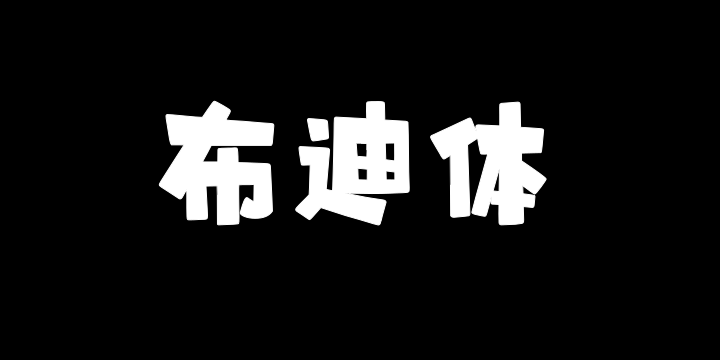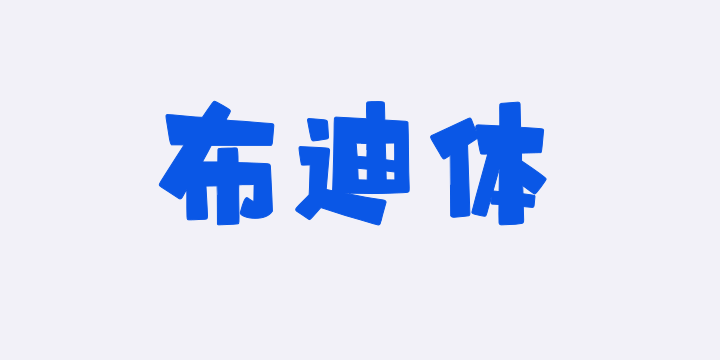
字体全名: 上首布迪体
铸字厂: 上首造字
设计师: 胡博剑
字体简介: 上首布迪体,简体中文约6763字,字体以pop字体为原型参考,字形设计注重动态感与趣味性,常通过拉伸笔画、立体效果和幽默造型吸引注意力。例如,活体字笔画向内聚拢,半包围结构字体需营造“馅比皮大”的视觉效果。 简洁性 信息传达需一目了然,避免复杂结构导致辨识困难。字体设计强调几何化处理,减少笔画细节,突出核心信息。字体偏向于卡通、可爱的风格。字体特点鲜明,适用于搭配标志、广告标语、商业广告、海报字体等高端属性。